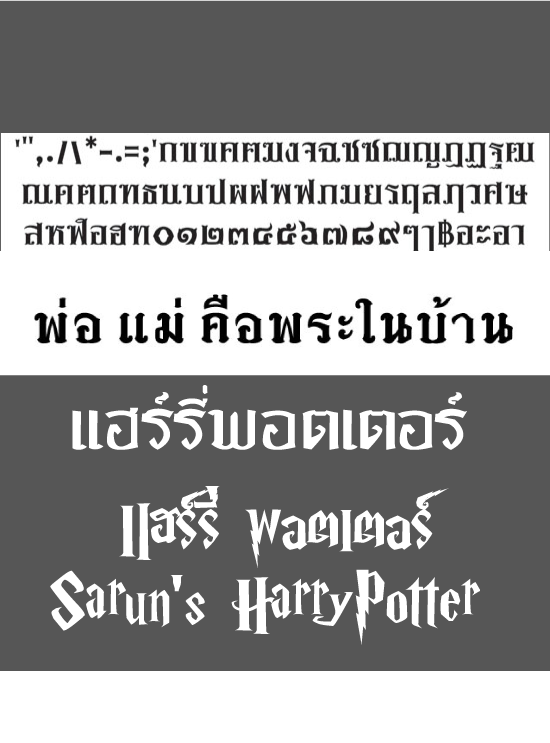
รัฐพล ฟอนต์
เป็นฟอนต์ที่ทำขึ้นมาเพื่อสนอง need ตัวเองชัดๆโดยตั้งชื่อตัวเอง ไร้การ sketch และแรงบันดาลใจ สดๆเรื่อยๆจาก Illustrator ดีเทลไม่ละเอียด หนาบ้าง บางบ้าง สงสัยจะทำตามใจไปหน่อย :43: ข้าพเจ้าทำฟอนต์ตัวนี้เป็นตัวที่ 2 (หลังจากคอนเซปต์ฟอนต์ ส.เสือ ที่ยังไม่มีให้โหลดในเร็วๆนี้ เพราะความผิดพลาดบางอย่าง จึงได้ทำการนับหนึ่งอีกครั้งโดยครั้งบรรจุลง NaipolTemplate โดยพลัน ก็ไม่แล้วเสร็จ...!!) และความมันมือ+อารมณ์ศิลป์ไม่เคยปราณีใครหันมาเขียนฟอนต์ตัวนี้ไว้ล่วงหน้าซะอีก คาดว่าจะได้ความสมบูรณ์ในอนาคตเช่นกัน.. :58:   :44:
สวยยยยย
แต่ผมชอบตัวที่แล้วด้วยนะ บ้าบอดี :30:
เก๋ดีนะ  :25:
ตัวเลข 2 ไทย ถ้ามันตัวเล็กๆ ขีดฐานด้านล่างของตัวเลข 2 ไทย มันจะหายไปหรือเปล่าครับ ลองพิมพ์ตัวเล็กๆดูสิ   :27:
แต่ฟอนต์ตัวนี้มันตคุ้นๆ จริงๆ นะครับ
มีแบบในหัวมาจากฟอนต์ไหนหรือเปล่าเอ่ย
ผมว่าก็คล้ายกับฟอนต์ด้านล่างนี้นะครับ
อีกตัวที่ดราฟไว้ครับ
กรี๊ด ตัวนี้ชอบ :0705:
เพลินนิส ฟอนต์ น่ารักดีนะครับ  :25: